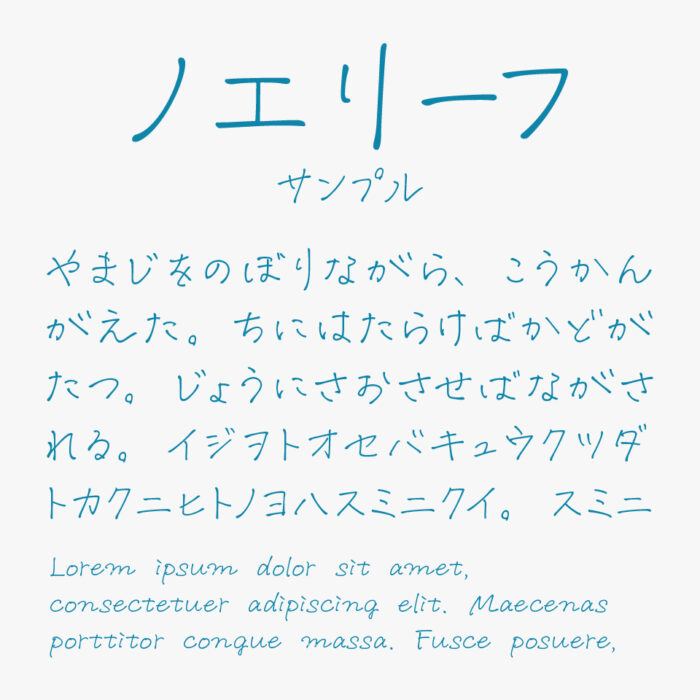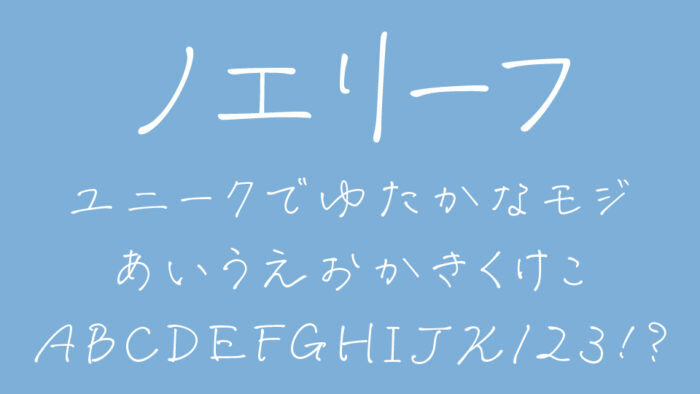
ノエリーフフォントは、万年筆で紙に書いた文字をスキャンして制作された手書き風フォントです。
紙に書いたインクのにじみが表現されていて、とても整った文字で、リアルな手書き感が息づかいを感じさせ、温かみのあるフォントとなっています。
収録文字は、ひらがな・カタカナ・アルファベット・数字・記号が収録されています。